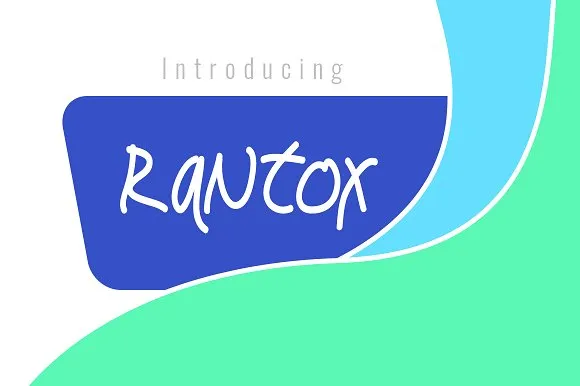
Rantox Typeface – Fonte Grátis
Rantox Typeface
Rantox é uma nova fonte que acaba de ser lançada por 178-MC. Nosso objetivo com este design foi criar uma fonte elegante e versátil, perfeita para um amplo espectro de projetos gráficos. Com seu estilo script, a Rantox se destaca como uma escolha ótima para aplicar em logotipos, roupas personalizadas, designs impressos, cabeçalhos de sites, painéis de fotos e capas de álbuns, entre outros. Seu design fluido proporciona um toque único e moderno a qualquer projeto, tornando-a uma opção indispensável para designers em todos os níveis. Acredito que você se sentirá contente ao experimentar essa nova adição à sua coleção de fontes.